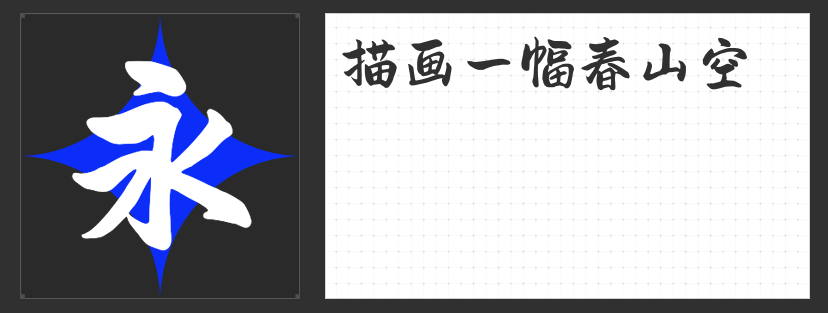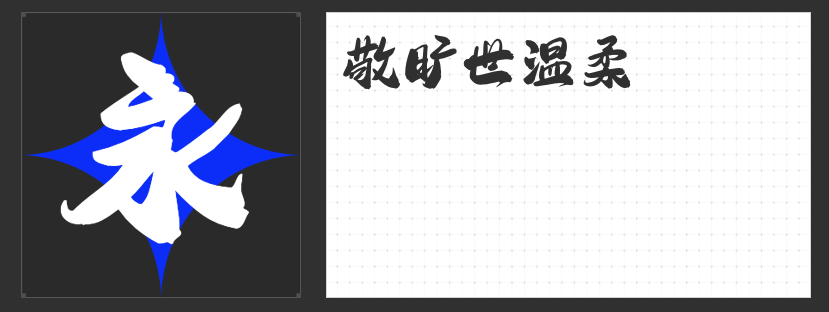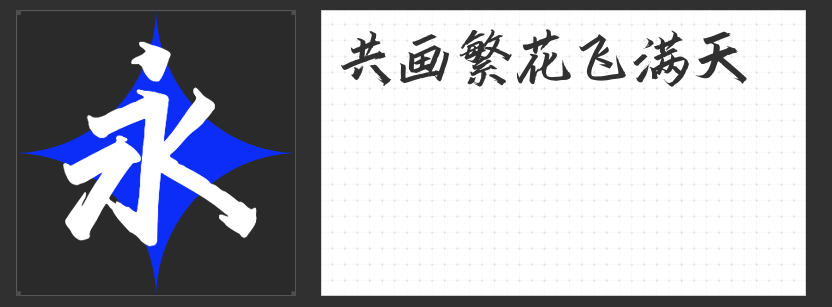
《唐朝诡事录》:穿越千年的谜团,古装悬疑剧中的字体推荐
在探索《唐朝诡事录》这一融合了历史韵味与悬疑元素的古装剧集时,字体的选择成为了构建氛围、增强故事代入感的关键要素。以下,我将为您推荐几款特别适合古装悬疑剧集设计的字体,它们不仅能够精准传达古典美,还能巧妙融入悬疑氛围。
这款字体笔画窈窕、秀丽,结构洒脱自然,用笔圆融,每个字中都有一画或多画点睛之笔,使字形饱满。其笔划流畅而不失力度,既能展现古代的繁华盛世,又暗含了剧中错综复杂的谜团,是标题设计或关键线索呈现的理想之选。
2.造字侠今朝醉简
以“今朝醉”命名的这款简体字体,透露出一种微醺而迷离的诗意美,恰似剧中角色在探寻真相过程中偶尔流露的迷茫与沉醉。其字形简约而不失韵味,适用于营造剧中氛围的旁白、注解或是场景转换的文字提示,增添一抹神秘色彩。
这款字体展现出一种独特的古朴与张力。它仿佛能引领观众穿越回那个风起云涌的朝代,感受每一次推理背后的惊心动魄。适合用于重要情节的标题、关键证据的展示或是角色内心独白的呈现,增强视觉冲击力与情感共鸣。
4.造字侠侠道简繁
侠之大道,义薄云天。这款字体以其独特的毛笔笔画,彰显了武侠世界的侠骨柔情与正义精神。在《唐朝诡事录》这样的古装悬疑剧中,它不仅是角色名、门派名称的绝佳选择,也能在关键时刻传递出角色间深厚的情谊与坚定的信念,让剧情更加引人入胜。
综上所述,无论是硬笔书法体古典美与神秘感,还是毛笔字体的动态美与力量感,这些字体都能为古装悬疑剧增添独特的魅力与韵味。它们不仅能够帮助观众更好地理解剧情、感受氛围,还能让整部剧集在视觉上更加出彩、更加引人入胜。